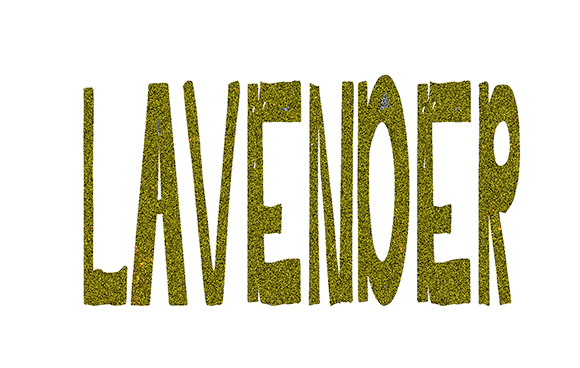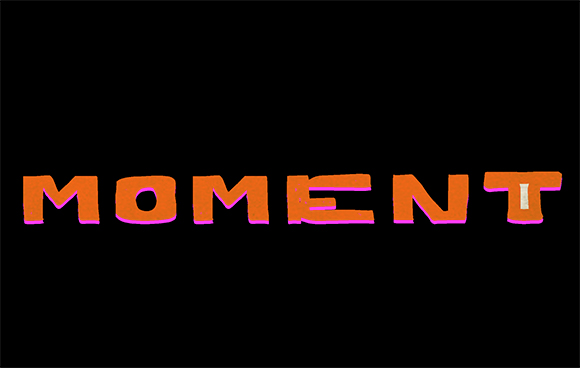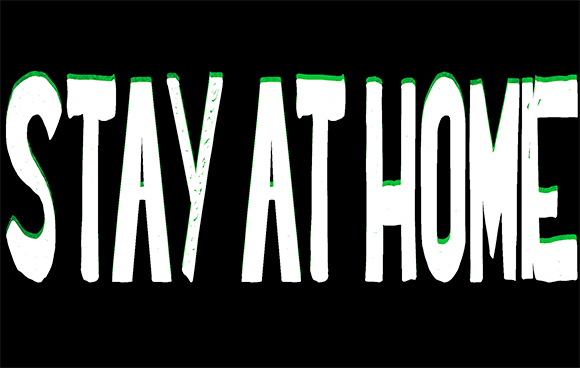
Steep Beauty Font
Font Tampilan Curam Kecantikan
Steep Beauty merupakan tampilan font yang didesain untuk kebutuhan undangan pernikahan, pengetikan, poster, sablon, sablon buku, mencari font untuk instagram. Font ini mengubah ide kreatif apa pun menjadi seni yang indah!